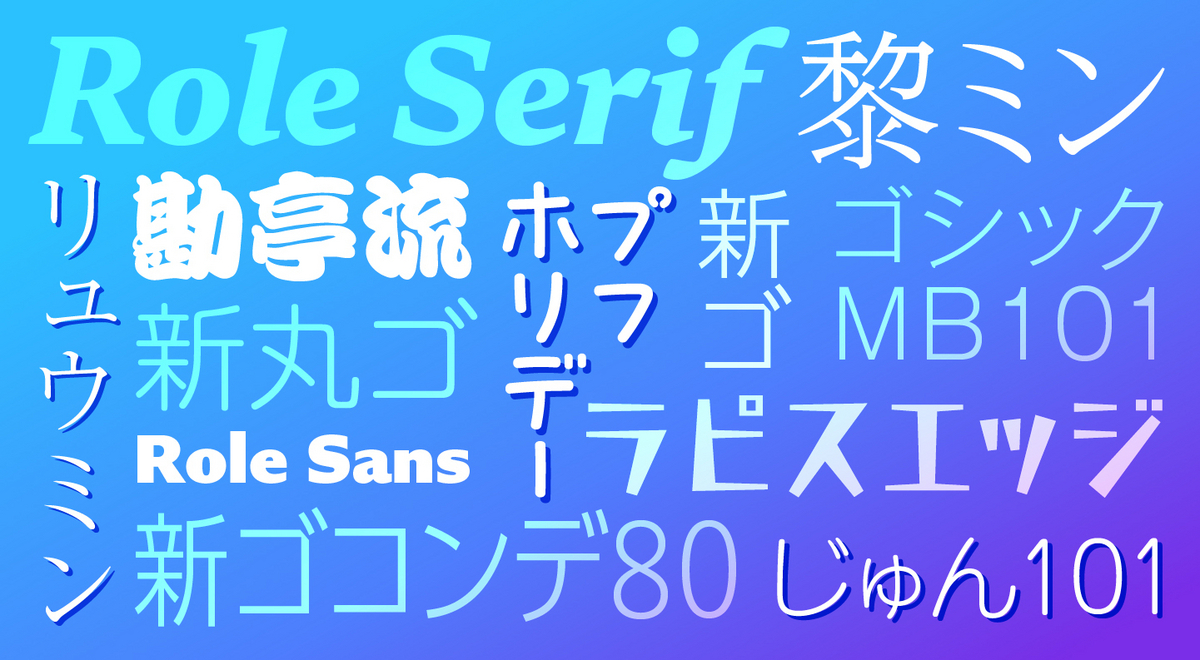
モリサワ ビジュアル・コミュニケーション・プラットフォーム「Canva」へ、UD新ゴや勘亭流など日本語フォントと欧文フォント Roleを提供開始
モリサワは、ビジュアル・コミュニケーション・プラットフォーム「Canva」に日本語フォント10書体、欧文フォント2ファミリーの提供を開始したことを2023年12月1日に発表した。
「Canva」は、オーストラリアのCanva Pty Ltdが2013年から提供を開始したオンラインデザインおよびビジュアルコミュニケーションのデザインプラットフォームで、提供した書体は、スタンダードな明朝体「リュウミン」やUD(ユニバーサルデザイン)フォントである「UD新ゴ」、近年ではうちわ文字としても人気の筆書体「勘亭流」など日本語10書体と、欧文フォント「Role」となる。
「Role」は4つのスタイルと3つのサイズシーンに最適化されたデザインのバリエーションを持つ、200書体を誇る欧文スーパーファミリーで、Role Serif Text ProとRole Sans Text Proの2つのファミリーから32書体を提供。
モリサワのフォントラインナップは、フォントメニュー名の冒頭に「Morisawa」と記載があるため探しやすくなっており、今後はこれらのフォントが、世界中のCanvaのデザインコミュニティで利用できるようになる。
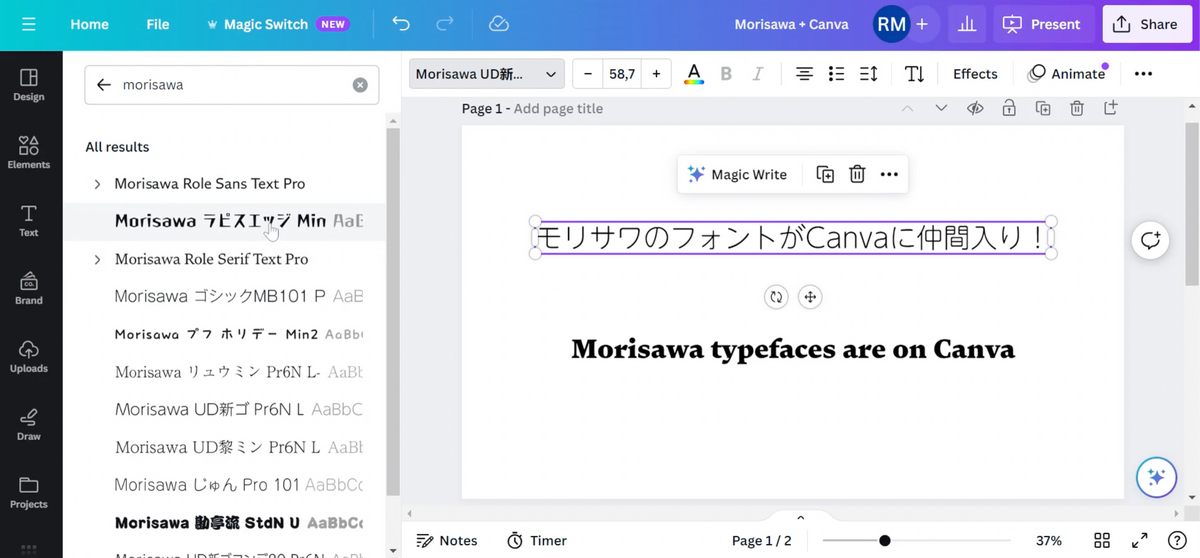
「Canva」モリサワフォント提供 概要
▼提供書体
リュウミン L-KL
じゅん 101
ゴシックMB101 L
UD新ゴ L
UD新丸ゴ L
UD黎ミン L
UD新ゴ コンデンス80 L
勘亭流
ラピスエッジ B
プフ ホリデー
Role Serif Text Pro
ExtraLight / ExtraLight Italic / Light / Light Italic / Regular / Italic / Medium / Medium Italic / Bold / Bold Italic / ExtraBold / ExtraBold Italic / Heavy / Heavy Italic
Role Sans Text Pro
Thin / Thin Italic / ExtraLight / ExtraLight Italic / Light / Light Italic / Regular / Italic / Medium / Medium Italic / Bold / Bold Italic / ExtraBold / ExtraBold Italic / Heavy / Heavy Italic / Black / Black Italic